1. BỘ PHÔNG CHỮ MOMO CHÍNH THỨC CÓ MẶT TRÊN GOOGLE FONTS
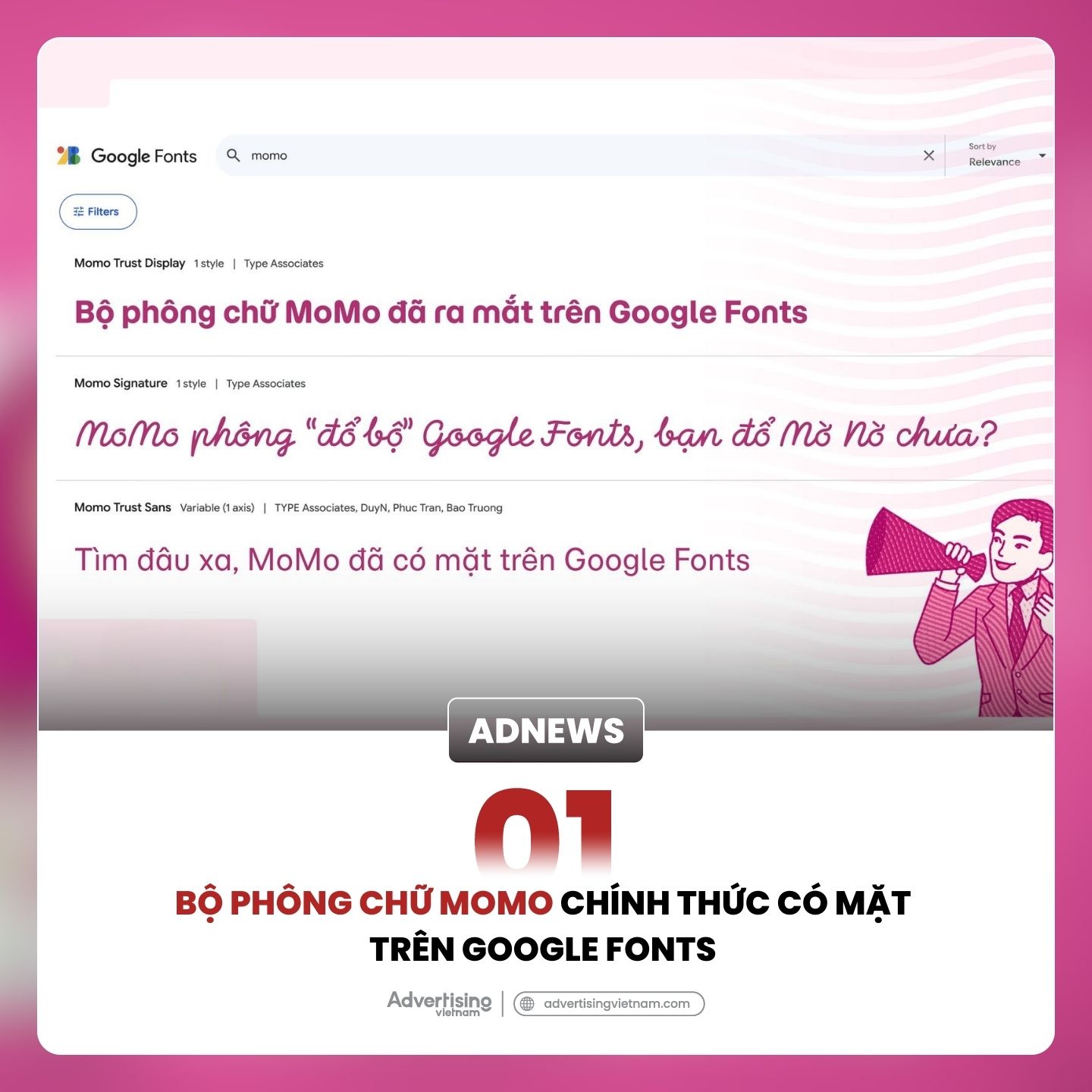
Vừa qua, bộ phông chữ MoMo đã chính thức có mặt trên Google Fonts, mang đến nét sáng tạo đặc trưng của Việt Nam cho hàng triệu nhà thiết kế trên toàn cầu.
Hệ thống phông chữ của MoMo, được thiết kế riêng bởi công ty Type Associates, bao gồm ba bộ phông được lấy cảm hứng từ chính logo MoMo và chữ viết tay của người dùng:
- MoMo Trust Display (kiểu chữ không chân cho tiêu đề) chỉ có 1 định dạng về độ dày.
- MoMo Trust Sans (kiểu chữ không chân) có 3 định dạng về độ dày: Đậm vừa (Medium), Thường (Regular) và Mỏng (Light).
- MoMo Signature (kiểu chữ viết tay) chỉ có 1 định dạng về độ dày.
Bộ phông này được đánh giá là một tổ hợp linh hoạt, tối giản và có tính ứng dụng cao, giúp củng cố nhận diện thương hiệu một cách thân thiện và nhất quán. Động thái này cho thấy sự đầu tư nghiêm túc của MoMo vào bộ nhận diện thương hiệu, đồng thời góp phần quảng bá văn hóa thiết kế Việt Nam ra toàn cầu.
Quán súp được đặt tại đảo Ersha, một địa điểm nổi tiếng và được xem là thiên đường của cộng đồng runner địa phương. Thực đơn tập trung vào các loại súp Quảng Đông truyền thống, bao gồm các nguyên liệu như vỏ quýt khô, khổ qua, táo tàu và sườn heo.
Thông điệp: “Không có nỗ lực nào là vô ích” đã tạo nên một điểm chạm cảm xúc mạnh mẽ, kết nối sự kiên trì, nỗ lực không ngừng trong chạy bộ với sự tỉ mỉ, kiên nhẫn trong quá trình nấu một món súp truyền thống.
Với quầy súp nhỏ, ghế nhựa đỏ và sự tối giản trong nhận diện, không gian này dường như chẳng liên quan đến Nike. Nhưng chính sự khác biệt đó lại là chiến lược mà thương hiệu theo đuổi. Nike không cố gắng bán sản phẩm hay phô trương quảng cáo, họ chọn cách hiện diện tự nhiên trong đời sống của người dùng, bằng cách phục vụ món ăn bổ dưỡng để các runner nạp lại năng lượng sau khi tập luyện.